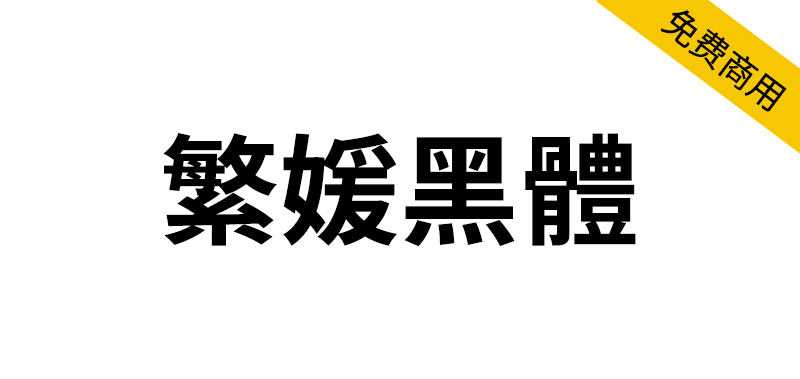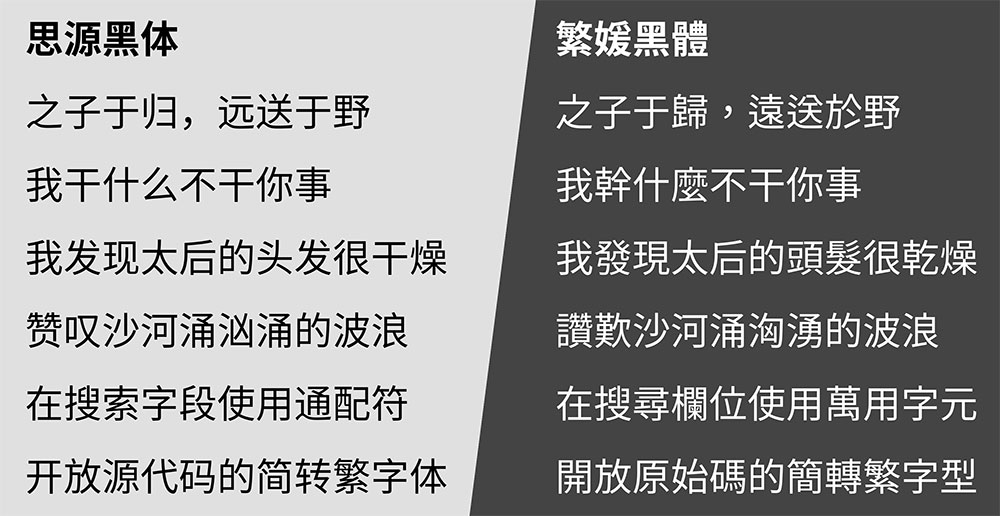
繁媛黑体(Fan Wun Hak)是基于源样黑体开发的简转繁字体,能处理「一简对多繁」。源样黑体是基于思源黑体的开放原始码字体。
注意:下载包里包含有两个版本,一个是FanWunHak,表示将简体中文字符转换为繁体中文字符,可以理解成是繁媛黑体的标准版或常用版,另外一个是FanWunHak-TW,表示转换成台湾短语/词语,例如输入鼠标显示滑鼠,但不太准确。